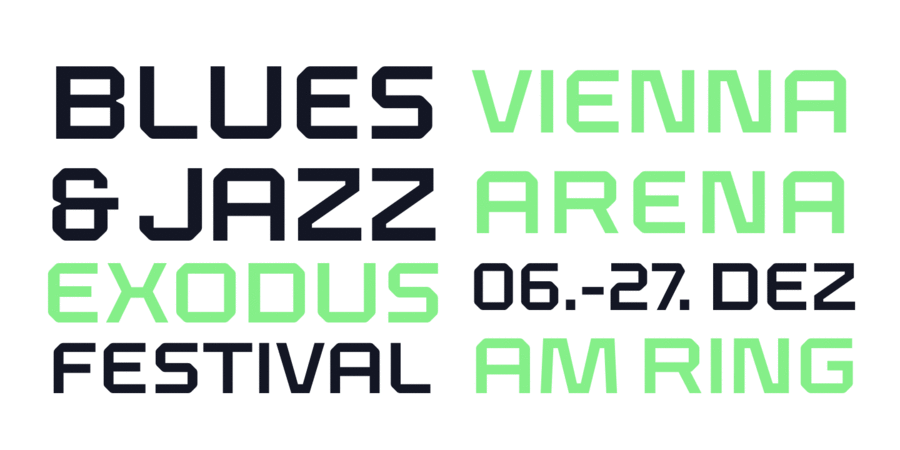
Klapt (4 шрифта)
Klapt – це геометричний ґротеск, пом'якшений зовні і гострий всередині. Це сімейство з чотирьох накреслень включає розширений набір символів, підтримує більшість латинських мов, і навіть в'єтнамську! Klapt, який може бути і жирним і дуже тонким, призначений для різного дизайну, від брендингу й фірмового стилю до багатосторінкових видань для друку та екранів. Він відмінно підходить для акціденціі, особливо для заголовків, постерів, журналів, обкладинок, логотипів. Не соромтеся ділитися своїми дизайнами з використанням Klapt чи просто зв'яжіться з автором hi@seventype.com. Шрифт розробила Віторія Невес у 2019 році.
Асоціації з сімейством шрифтів KlaptОсобистість і характер гарнітури:
рівний, квадратний, точний, логічний, холодний, автоматичний, техногенний, твердий, статичний, різкий, чіткий, стійкий, стабільний, тонкий, легкий, прямокутний, міський, сучасний, машинний, гострий, інженерний, урбаністичний, креслярський, скляний, крихкий, футуристичний, дротяний, Простий, надійний, впевнений, сталевий, космічний, байдужий, гранчастий, рубаний, переконливий, серйозний, сильний, індустріальний, залізний, мужній, військовий, армійський, промисловий, залізничний, ігровий, спортивний, робочий, кінематографічний
конструктор, креслення, архітектура, інженер, автоматика, урбаністика, наука, дизайн, Місто, статистика, гаджет, електроніка, технології, фантастика, космос, інструмент, робот, гра, прилад, айтішник, IT, айті, андроїд, залізо, коворкінг, рентген, астрономія, авто, промисловість, війна, армія, зброя, завод, металургія, верстат, тара, склад, порт, ящик, патрони, техніка, ремонт, депо, шолом, уніформа, вагон, авіація, літак, автомат, шутер, екшен, транспорт, страйкбол, взуття, залізниця, кубики, лего, комп'ютерна гра, спорт, машинобудування, охорона, захист, паливо, поліція, будівництво, цегла, автобус, робочий, кіно, кіберспорт Гарнітура має ознаки стилів: